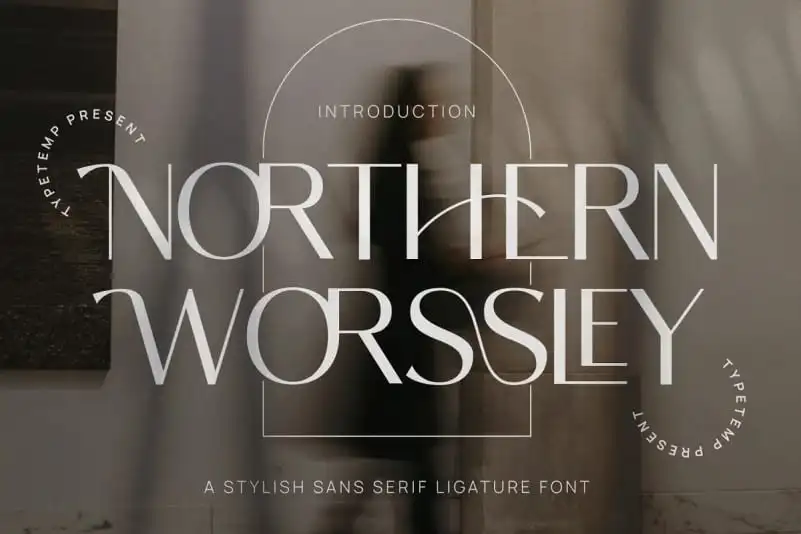
Northern Worssley Sans Serif Font – Download Grátis
A Northern Worssley Sans Serif Font é uma elegante fonte condensada projetada para criar designs contemporâneos e sofisticados. Com suas linhas curvas finas e traços delicadamente reduzidos, ela enriquece qualquer projeto gráfico com um toque de requinte e modernidade. Esta fonte foi cuidadosamente desenvolvida pelo studio Typetemp para que você possa aplicá-la em seus logotipos e layouts de forma rápida e eficiente. O design atento aos detalhes garante uma aparência fluida, perfeita tanto para textos quanto para aplicações visuais. Os recursos OpenType da fonte permitem a criação de efeitos especiais, como alternativas de letras e ligações mais complexas. Este é um recurso imprescindível para quem deseja personalizar ainda mais suas criações digitais com uma mistura de elegância e criatividade. Com essa fonte em sua coleção, seu trabalho pode ser distinguido por uma expressão única e impecável.